かわいい!少女マンガ・ファッションブック 昭和少女にモードを教えた4人の作家
インプレスグループで文芸・料理関連の出版事業を展開する立東舎は、倉持佳代子氏、図書の家著書「かわいい!少女マンガ・ファッションブック 昭和少女にモードを教えた4人の作家」を2020年2月14日に発売しました。
昭和30年代から40年代の少女マンガ作品や雑誌には、当時の少女たちの心を躍らせたすてきなファッションのイラストが多数掲載されていた。
「かわいい!少女マンガ・ファッションブック 昭和少女にモードを教えた4人の作家」では、そんな「ファッション画」を、牧美也子氏、わたなべまさこ氏、北島洋子氏、谷ゆき子氏を中心に160点以上ピックアップして再構成し、当時の大人気マンガ家へのインタビュー、専門家による解説など、全ページ・オールカラーで紹介。総図版300点を超える、資料としても大変貴重な1冊になっている。また、当時のふろくを彷彿させる「着せ替え人形カード」もついている。
少女マンガを通して少女読者のおしゃれをリードしていた、牧美也子氏。大人気だった赤いコートだけを集めたページも。同じ赤でもバリエーションが豊富。
ゴージャスなお話が多く、描くファッションも華やかな、わたなべまさこ氏。帽子やヘアアクセサリーも豪華。ロイヤルファッションも多数収録されている。
パンタロンやミニスカートなど、当時最先端のファッションも取り入れ、新風を吹き込んだ、北島洋子氏。すらりと伸びた長い足、コミカルなポーズで決めたヒロインは今見てもかわいくてかっこいい。
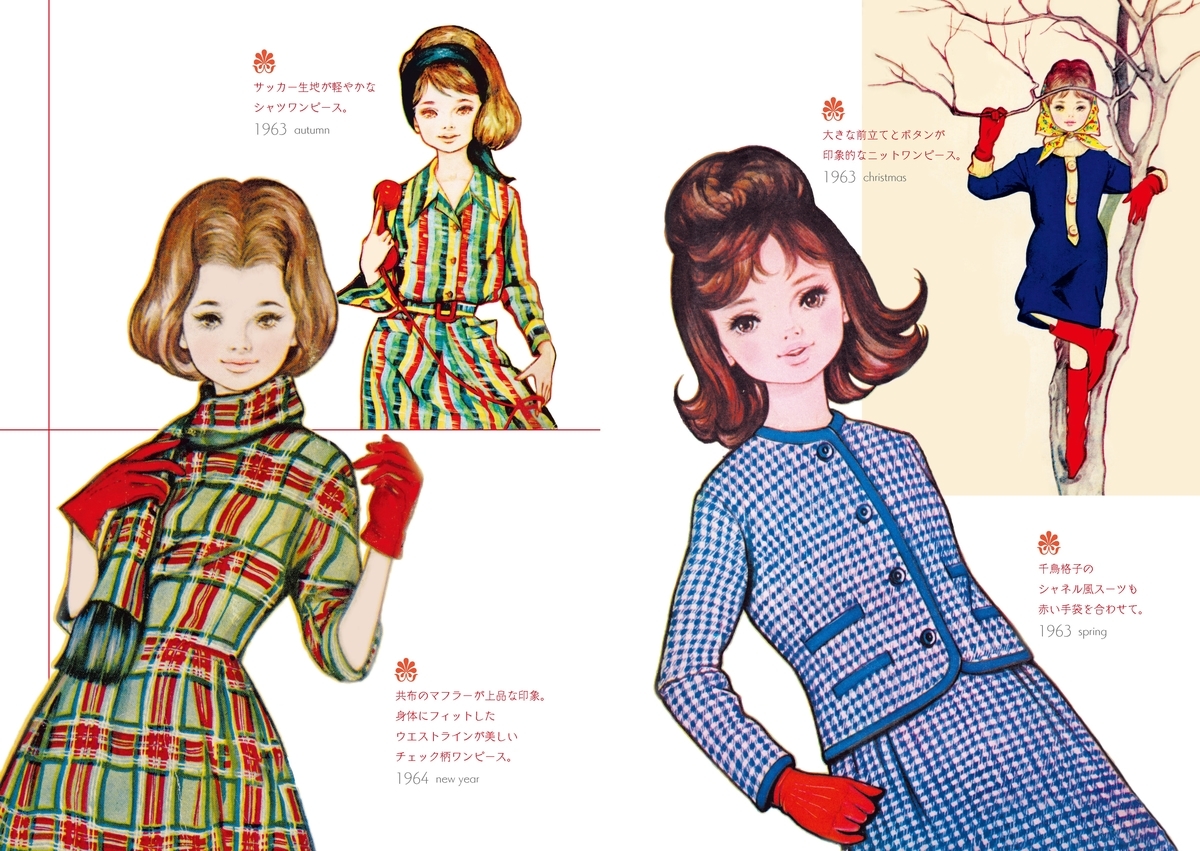
昭和30~40年代に大阪で刊行された貸本単行本『すみれ』『虹』などの表紙絵を担当した谷ゆき子氏。昨今、バレエマンガの復刻シリーズで話題になっている作者ですが、こちらの才能にも注目。
昭和少女を取り巻く実際のファッション事情はどうだったのか? ファッションと少女マンガの深い関係を解き明かす専門家対談も掲載。
倉持佳代子Profile●京都国際マンガミュージアム研究員。主に少女マンガを研究対象として、多数のマンガに関する展覧会やイベントを担当。同館では2011~2014年まで、「少女マンガ」からインスピレーションを得た衣類の開発プロジェクト「Kyoto Manga Girls Collection」(略称;Kyoto MaGiC)に携わり、戦前から現在までの少女マンガの流れを見せるべく、ファッションショーや展覧会を企画した。また、マンガに関するコラムを新聞雑誌に寄稿するなど執筆活動も行っている。2016年に刊行された『超展開バレエマンガ 谷ゆき子の世界』(立東舎)では編集協力として執筆に関わっている。
図書の家Profile●1999年、少女マンガ研究サイト「図書の家」を開設、現在は少女マンガに関する書籍の企画編集制作、デザイン、映像制作などを行っている。初出調査・作家検証は自己所有資料を含め実資料にあたることを身上としている。立東舎での主な実績は、『超展開バレエマンガ 谷ゆき子の世界』『少女マンガの宇宙』、 谷ゆき子著『バレエ星』『まりもの星』『さよなら星』、飛鳥幸子著『決定版! 怪盗こうもり男爵』。 少女マンガ家の仕事をまとめた「総特集シリーズ」を 河出書房新社より出している。
直近では『総特集 わたなべまさこ?90歳、今なお愛を描く?』を 『わたなべまさこ名作セレクション?花と洋館とファッションと?』(「花の館」ほか収録)と同時刊行した。
「かわいい!少女マンガ・ファッションブック 昭和少女にモードを教えた4人の作家」目次
牧美也子ファッションブック
・インタビュー「普遍的なファッションを」
わたなべまさこファッションブック
・インタビュー「お話そのものがゴージャスなので」
北島洋子ファッションブック
・インタビュー「素材は頭に置いて描いていました」
谷ゆき子ファッションブック
・コラム「谷ゆき子、その仕事とファッション」
専門家対談「ファッションと少女マンガ、その関係 ~昭和少女を取り巻くファッション事情とは~」
筒井直子/京都服飾文化研究財団(KCI)×倉持佳代子/京都国際マンガミュージアム研究員
イラストINDEX
あとがき「少女マンガとファッションがくれた宝物」倉持佳代子
少女マンガチックな乙女な書体「優雅宋」紹介記事